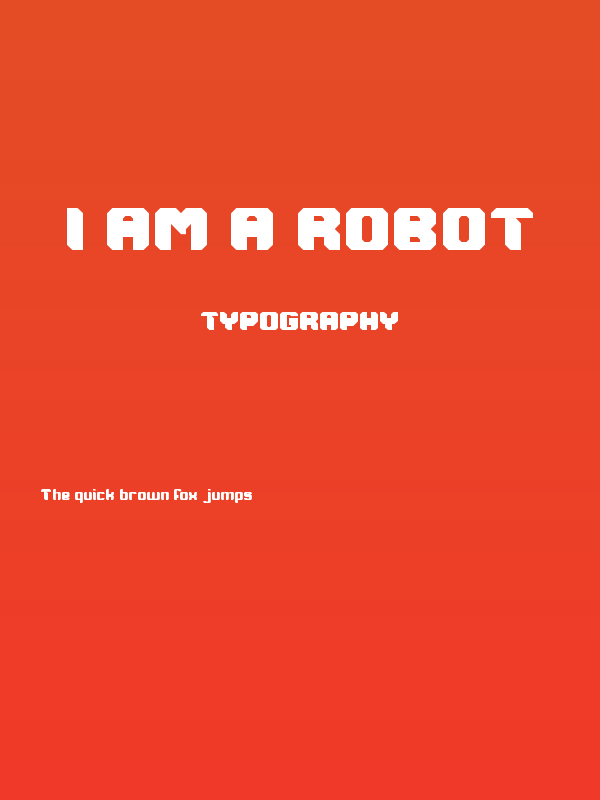
I AM A ROBOT Font
| Stile generale | Futuristic, Industrial |
| Progetti proposti | Ideal for technology branding, sci-fi movie posters, video game titles, and futuristic-themed designs. |